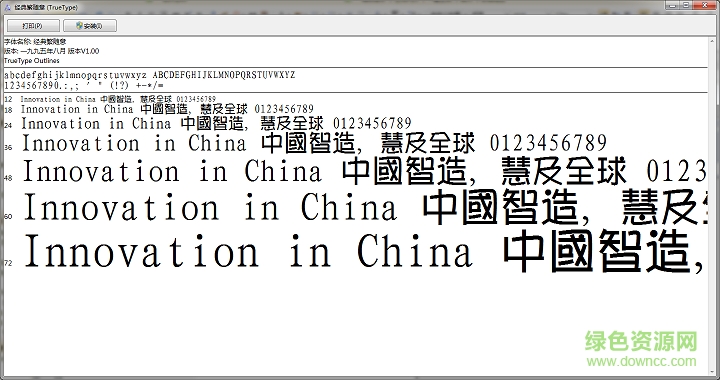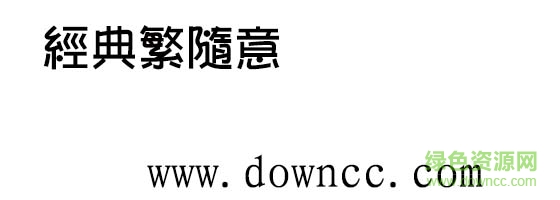
1.中國的字體設(shè)計(jì)是在印刷術(shù)的產(chǎn)生和發(fā)展中應(yīng)運(yùn)而生的。在古代,中國的字體設(shè)計(jì)曾有過輝煌的歷史時期,在宋朝時進(jìn)入黃金時代。
2.清朝末年,鉛字排版印刷術(shù)傳入中國,字體設(shè)計(jì)進(jìn)入鉛字時代。這個時期的字體設(shè)計(jì)既要帶有傳統(tǒng)文化的審美慣性,又要符合鉛字印刷的工藝要求,字體設(shè)計(jì)走到了轉(zhuǎn)折的關(guān)口。
3.鉛字印刷是印刷走入機(jī)械化、工業(yè)化時代的標(biāo)志,但在這一時代里,印刷字體設(shè)計(jì)卻始終無法超越手工勞動的制約,無法擺脫刻模、鑄字、撿字、排版等一系列印前繁雜工藝的束縛